Trong thiết kế kiến trúc và đồ họa, các bộ font chữ không chân viết tay mang đến sự giao thoa độc đáo giữa tính mạch lạc của phông chữ hiện đại và tâm hồn của nét bút thủ công. Khác với những kiểu chữ in ấn công nghiệp vốn có phần khô cứng, dòng phông này mô phỏng lại nhịp điệu tự nhiên của người viết nhưng vẫn giữ được cấu trúc tinh gọn, không có các nét gạch nhỏ ở đầu ký tự.
Đặc điểm thẩm mỹ của dòng font chữ không chân viết tay trong thiết kế
Nét lôi cuốn đặc trưng của phông chữ không chân viết tay nằm ở sự cân bằng giữa tính hình học và cảm giác nhân bản. Các đường nét thường có độ dày đồng nhất theo phong cách Sans-serif nhưng lại sở hữu những đường bo góc ngẫu hứng, mô phỏng sinh động các vệt mực của bút dạ hoặc bút lông.
Sự ổn định của dòng font này còn thể hiện ở khả năng truyền tải năng lượng tích cực và sự thư giãn cho người xem. Trong các không gian kiến trúc hiện đại, việc ứng dụng các kiểu chữ viết tay không chân giúp làm dịu đi sự thô cứng của các khối kết cấu thép hay tấm panel phẳng. Đây là phương án hiệu quả để định hình phong cách cho các dự án nghỉ dưỡng, nhà lắp ghép xanh hoặc những thương hiệu muốn khẳng định sự thân thiện, năng động và tư duy đổi mới.
| Phân loại phong cách | Handwritten Sans-serif / Casual Script |
| Mục đích phù hợp | Logo homestay, tiêu đề poster, ghi chú phối cảnh |
Tư vấn lựa chọn: Phông chữ viết tay không chân phát huy hiệu quả thị giác tốt khi bạn sử dụng cho các tiêu đề ngắn hoặc câu slogan quan trọng. Việc phối hợp cùng một phông chữ không chân tiêu chuẩn (như Roboto hay Montserrat) cho phần nội dung chi tiết sẽ giúp tổng thể bản thiết kế trở nên chuyên nghiệp và dễ đọc hơn.
03 Ứng dụng phông chữ viết tay không chân vào kiến trúc
Nhờ vẻ ngoài giàu tính thẩm mỹ và cá tính, bộ phông chữ này mang lại giá trị thực tế cao trong khâu trang trí và quảng bá các công trình xây dựng hiện đại:
- Hệ thống biển hiệu cho Homestay & Cafe: Những nét chữ viết tay gọn gàng rất ăn ý khi xuất hiện trên biển hiệu mica gương hoặc gỗ phủ màu pastel tại các khu nhà lắp ghép nghỉ dưỡng. Font chữ này giúp không gian toát lên vẻ trẻ trung, thu hút du khách yêu thích sự mới mẻ.
- Trang trí không gian nội thất sáng tạo: Bạn có thể dùng font này để làm tranh quotes trang trí hoặc cắt chữ nổi đèn neon tại phòng khách, khu vực thư giãn trong văn phòng container nhằm tạo điểm nhấn lôi cuốn và khơi gợi cảm hứng làm việc.
- Ghi chú nghệ thuật trên bản vẽ phối cảnh: Sử dụng font chữ không chân viết tay để trình bày các diễn giải ý tưởng kiến trúc giúp bản vẽ trông có hồn hơn, thể hiện sự tinh tế và tận tâm của người kiến tạo đối với khách hàng.
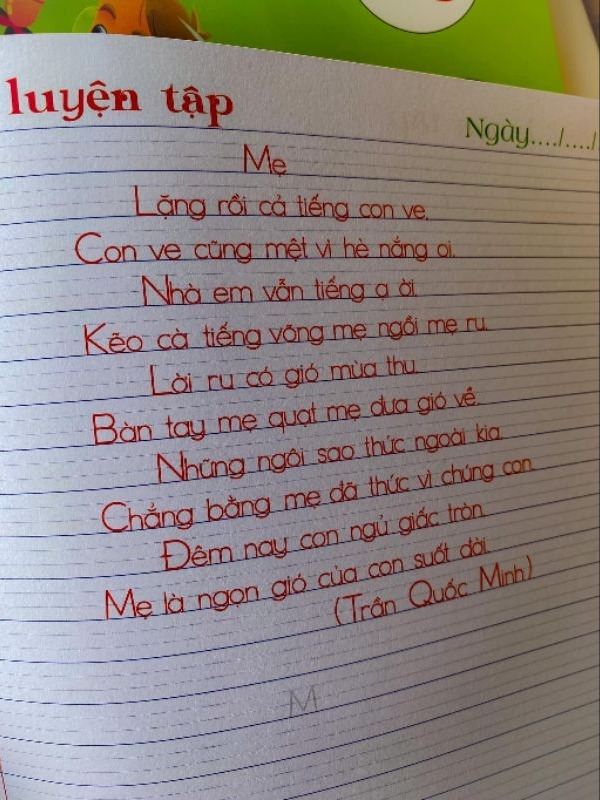
03 Lưu ý kỹ thuật để bố cục phông chữ viết tay không chân chỉn chu
Để khai thác vẻ đẹp của dòng font đặc thù này mà không làm giảm tính chuyên nghiệp của bản thiết kế, người thiết kế nên lưu tâm một số kinh nghiệm sau:
- Kiểm soát khoảng cách dòng: Do cấu trúc chữ viết tay có xu hướng uốn lượn nhịp nhàng, bạn nên nới rộng khoảng cách giữa các dòng một chút để các nét chữ không bị chồng lấn, giữ được sự minh bạch cho văn bản khi nhìn từ xa.
- Hạn chế viết hoa toàn bộ ký tự: Đặc trưng của font viết tay là sự liên kết mềm mại giữa các chữ thường. Việc viết hoa toàn bộ cụm từ sẽ làm mất đi nhịp điệu tự nhiên và làm cho tiêu đề trở nên thô cứng, thiếu thẩm mỹ.
- Lựa chọn kích thước hiển thị phù hợp: Tránh sử dụng các phông chữ này ở kích thước quá nhỏ trên các bảng thông số kỹ thuật, vì nét chữ mô phỏng viết tay có thể gây khó đọc nếu mật độ ký tự quá dày đặc.